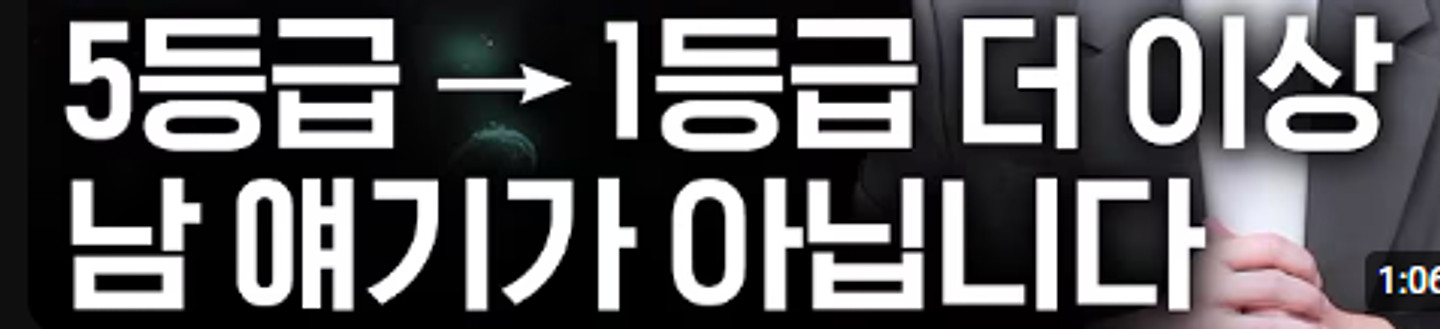
이거 무슨폰트인가요?? 메모먼트 꾹꾹체 인가 싶었는데 아니더라구요
SD 흐루링
폰트 찾을 수 있을까요? 그냥 인터넷에서 주운 이미지인데.. 괄호가 완전 둥그스름 형태가 아니고 살짝 각이 있는 특징이 있습니다 ㅠㅠ
혹시 어떤 폰트인지 아실까요?ㅠㅠㅠ
이거 무슨 폰트 인가요?! 프리텐다드와 노토산스는 아닙니다ㅜ